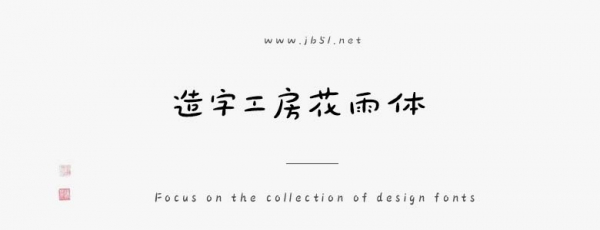
造字工房花雨體由上首造字字庫出品的字體,字體筆畫自然流暢,突出了字體的松弛感。字體結(jié)構(gòu)優(yōu)美靈動,風(fēng)格清新,適合應(yīng)用于平面宣傳設(shè)計(jì)、網(wǎng)頁設(shè)計(jì),書法字帖等領(lǐng)域,需要的朋友可以前來本站下載。
造字工房花雨體是一款小清新風(fēng)格的手寫體。筆畫自然流暢,突出了字體的松弛感。字體結(jié)構(gòu)優(yōu)美靈動,風(fēng)格清新,層次豐富賞心悅目。本字體為簡體字庫,采用OpenType/CID格式,Adobe-GB1-5編碼?;谥腥A人民共和國GB2312-80字符集標(biāo)準(zhǔn),另按需添加101個漢字。共收容字?jǐn)?shù)6864CJK漢字,ASCII常用字符100個。